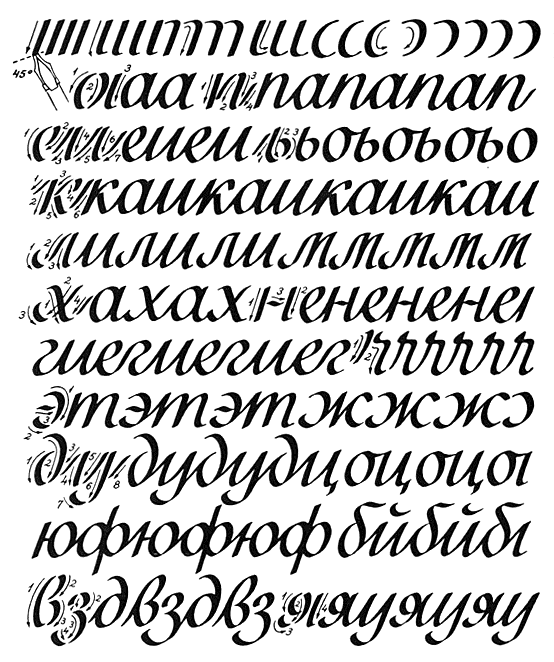
50 лучших бесплатных каллиграфических и курсивных шрифтов для дизайнеров 2023
Компания лучшая бесплатная каллиграфия, курсивные шрифты которые вы можете использовать в своем проекте. Типографика — один из самых важных факторов, когда дело доходит до дизайна, и здесь у нас есть несколько лучших вариантов шрифтов.
Другими словами, мы можем представить курсивные шрифты как рукописные шрифты или рукописные шрифты, которые придадут вашему дизайну естественный и привлекательный вид.
Мы уже перечислили лучшие скриптовые шрифты где вы найдете отличные варианты шрифтов. Курсивные шрифты существуют уже давно, и они будут оставаться очень важной частью даже современного дизайна.
Как правило, мы видим использование курсивных шрифтов в романах, письмах и других проектах, которые хотят использовать рукописные шрифты.
Использование курсивных шрифтов распространено среди мастеров боди-арта и татуировщиков.
Мы уже публиковали статью, чтобы продемонстрировать лучшие шрифты татуировки где вы также найдете несколько красивых курсивных шрифтов.
Мы используем курсивные шрифты со школьных времен, и эти шрифты наиболее актуальны даже сегодня. И самое приятное то, что существует множество замечательных источников, где можно найти бесплатные курсивные шрифты, которые вы можете скачать и использовать в своих проектах.
Что такое курсивные шрифты?
Курсивные шрифты обычно представляют собой рукописные шрифты с присоединяющимися буквами.
Мы используем шрифты Cursive в течение длительного времени, и он продолжает оставаться одним из наиболее широко используемых типов шрифтов.
Шрифты Cursive — это лучший вариант для творческих проектов, дизайна логотипов и любых надписей, требующих привлекательного вида.
Рукописные шрифты считаются шрифтами Cursive и различаются в зависимости от стиля и сложности письма.
Курсивные шрифты наиболее широко используются для создания обоев, рекламных слоганов, поздравительных открыток, рекламные щиты, графический дизайн и подобные проекты.
Итак, без дальнейших промедлений, давайте посмотрим на некоторые из лучших бесплатных курсивных шрифтов.
Аризония шрифт
Аризония красивый современный шрифт, который можно использовать для любого сценария. Вы можете использовать этот шрифт для любого рекламного щита, рекламных проектов, поздравительных открыток или даже для логотипов.
3. Курсивные шрифты умирают?Очень небольшая часть взрослых использует скоропись в повседневном письме. Тем не менее, исследователи указали, что учащиеся изучают некоторую форму чистописания наряду с цифровым. Утверждая, что умирающая форма скорописи, возможно, рассматривается как скорее эволюционировавшая в цифровой мир из-за физической формы ее формы.